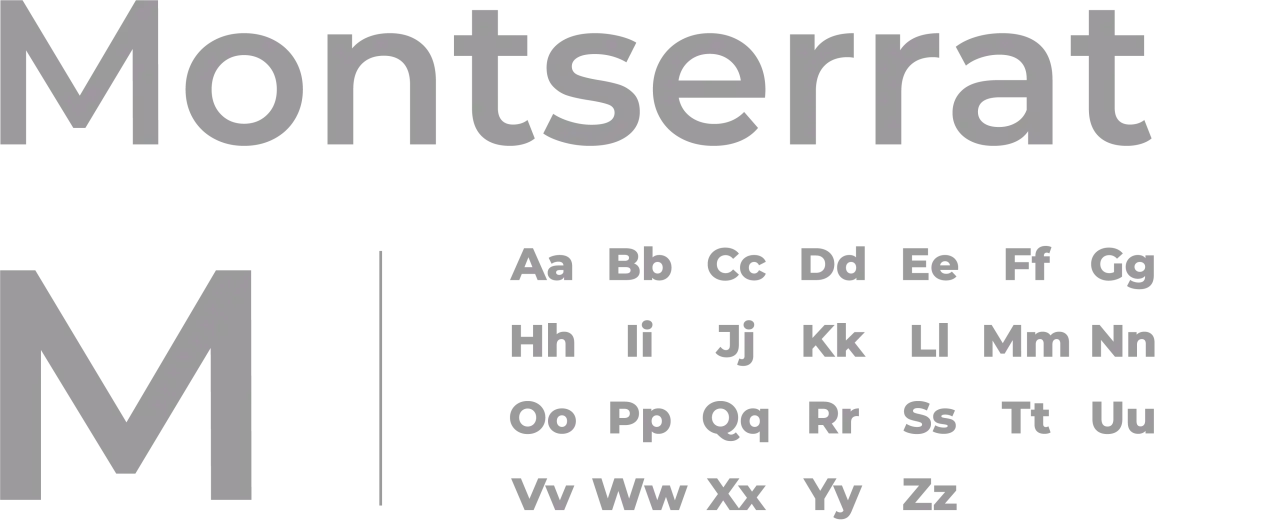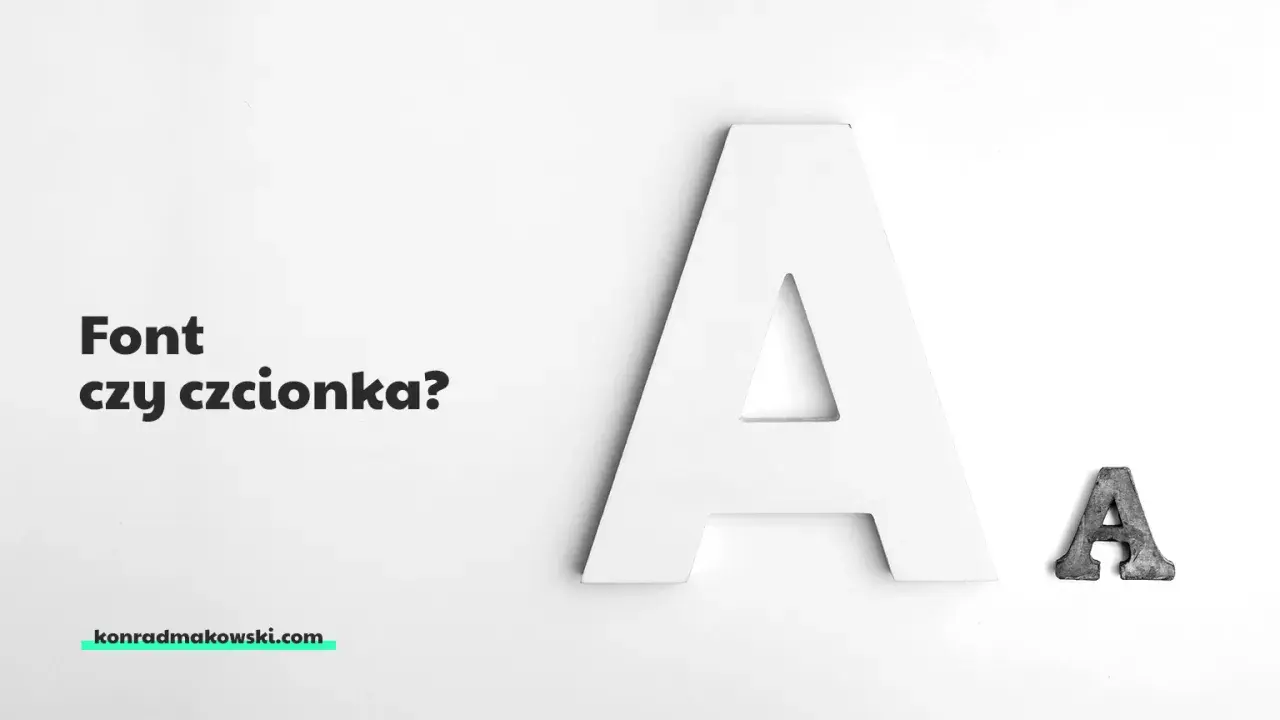
Najważniejsze rzeczy, które warto wiedzieć o fontach i typografii
- Font to cyfrowa wersja kroju pisma, a w potocznym języku słowa „czcionka” i „font” bywają mieszane, choć technicznie nie znaczą dokładnie tego samego.
- Najlepszy wybór zależy od celu: inaczej dobiera się krój do logo, inaczej do strony internetowej, a inaczej do reklamy lub raportu.
- O jakości fontu decydują nie tylko „ładne litery”, ale też czytelność, odstępy, obsługa polskich znaków, zakres odmian i licencja.
- W praktyce najbezpieczniej działa prosty zestaw: jeden krój do nagłówków, jeden do tekstu podstawowego, z jasno zdefiniowaną hierarchią.
- Najczęstsze błędy to nadmiar krojów, słaby kontrast, dekoracyjność kosztem czytelności i brak testu na małym ekranie.
Co właściwie oznacza font i gdzie kończy się czcionka
W rozmowie codziennej „czcionka” i „font” funkcjonują niemal jak synonimy, ale w projektowaniu warto znać różnicę. Font to cyfrowa postać kroju pisma, czyli konkretny zestaw znaków w określonej odmianie, wadze i stylu. Czcionka historycznie oznaczała fizyczny element drukarski, a dziś to rozróżnienie bywa rozmyte, bo większość osób używa obu słów zamiennie.
Ja patrzę na to tak: jeśli pracujesz nad identyfikacją wizualną, stroną internetową albo reklamą, ważniejsze od sporu o termin jest to, czy rozumiesz trzy poziomy typografii. Najpierw masz krój pisma, czyli sam projekt liter. Potem dochodzi font, czyli konkretna cyfrowa odmiana. Na końcu jest typografia, czyli sposób użycia tych liter w układzie tekstu: rozmiary, odstępy, interlinia, hierarchia i rytm.
| Pojęcie | Znaczenie w praktyce | Dlaczego to ważne |
|---|---|---|
| Czcionka | Historyczny nośnik pisma, dziś często używany potocznie | Pomaga rozumieć starsze opracowania i drukarską tradycję |
| Krój pisma | Projekt liter o określonym wyglądzie | To baza, na której budujesz styl tekstu |
| Font | Cyfrowa odmiana kroju, np. regular, bold, italic | To z tego korzystasz w programach, na stronie i w druku |
| Typografia | Sposób układania i używania tekstu | Decyduje o czytelności i charakterze komunikacji |
To rozróżnienie nie jest akademicką ciekawostką. Jeśli rozumiesz je poprawnie, łatwiej rozmawiasz z grafikiem, szybciej oceniasz szablon i trafniej wybierasz narzędzia do pracy. A gdy terminologia jest już uporządkowana, można przejść do pytania najważniejszego: jak dobrać krój do konkretnego zadania.
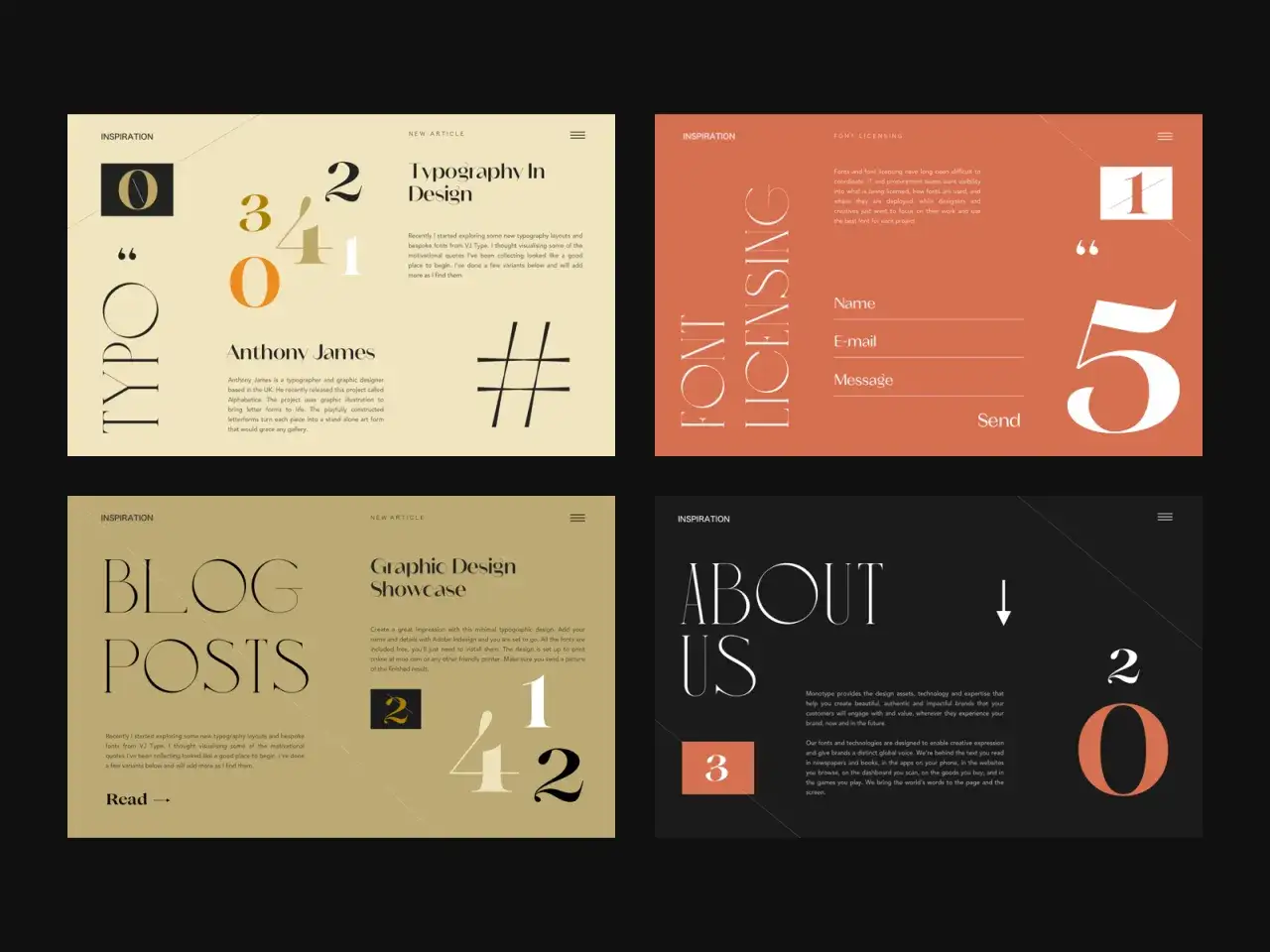
Jak dobrać font do projektu, żeby wspierał przekaz
Najlepszy font nie jest „najładniejszy” w oderwaniu od kontekstu. Jest taki, który pasuje do celu, medium i odbiorcy. Inaczej dobiera się krój do kancelarii prawnej, inaczej do marki kosmetycznej, a jeszcze inaczej do kampanii promocyjnej w social mediach. W typografii liczy się nie tylko estetyka, ale też to, jaki sygnał wysyłasz jeszcze zanim ktoś zacznie czytać.
Przy wyborze zadaję sobie zwykle kilka prostych pytań:
- Czy tekst ma budować zaufanie, energię, luksus, nowoczesność czy lekkość?
- Czy będzie czytany głównie na telefonie, monitorze, w druku, czy na opakowaniu?
- Czy potrzebuję fontu dyskretnego, czy takiego, który sam w sobie tworzy charakter?
- Czy projekt ma działać w długim tekście, czy tylko w krótkim haśle?
- Czy krój dobrze znosi małe rozmiary, wielkie nagłówki i różne grubości?
W praktyce nie warto zaczynać od ozdobnych detali. Najpierw wybieram krój, który dobrze działa funkcjonalnie, a dopiero później sprawdzam, czy ma odpowiednią osobowość. To podejście jest nudniejsze niż polowanie na efektowny font, ale znacznie bezpieczniejsze. W brandingowych i reklamowych projektach ten porządek pracy oszczędza mi później wielu korekt.
Dobry test jest prosty: wstaw ten sam tekst w kilku krojach, zmień rozmiar, przeglądaj na telefonie i na dużym ekranie. Jeśli po kilku sekundach jedna wersja nadal czyta się naturalnie, a druga zaczyna męczyć wzrok albo rozpraszać, wybór zwykle sam się ujawnia. To prowadzi prosto do cech, które trzeba oceniać nie na oko, lecz świadomie.
Na jakie cechy patrzeć przed wyborem
Wybierając font, łatwo zatrzymać się na pierwszym wrażeniu. To błąd, bo o wartości kroju decydują parametry, które widać dopiero po dłuższym spojrzeniu. Najważniejsze z nich to kontrast, wysokość x, światło wewnątrz liter, szerokość znaków, odstępy i kompletność zestawu znaków.
Najbardziej praktyczne cechy, które sprawdzam, to:
- Czytelność - litery muszą być rozpoznawalne również w małym rozmiarze.
- Kontrast kresek - duży kontrast bywa elegancki, ale na ekranie lub w drobnym tekście potrafi się rozsypywać.
- Odstępy między znakami - kerning i tracking wpływają na to, czy tekst oddycha, czy się zlepia.
- Zakres odmian - regular, italic, bold, semibold, light; bez tego trudno zbudować sensowną hierarchię.
- Polskie znaki - bez poprawnych ogonków nawet dobry krój przestaje być użyteczny w polskiej komunikacji.
- Licencja - font może być świetny wizualnie, ale niekoniecznie wolny do użycia w komercji lub w webie.
- dobierz jeden wyróżnik do nagłówków albo akcentów,
- sprawdź działanie na telefonie, w druku i w małej skali,
- na końcu upewnij się, że font ma pełne wsparcie dla polskiego tekstu i właściwą licencję.
To właśnie ta konsekwencja odróżnia estetyczną przypadkowość od dobrej typografii. Gdy wybór fontu wynika z funkcji, a nie z impulsu, cała komunikacja staje się czytelniejsza i bardziej wiarygodna. W praktyce najlepszy efekt daje nie najbardziej efektowny krój, lecz ten, który najczytelniej porządkuje treść i wzmacnia charakter marki.